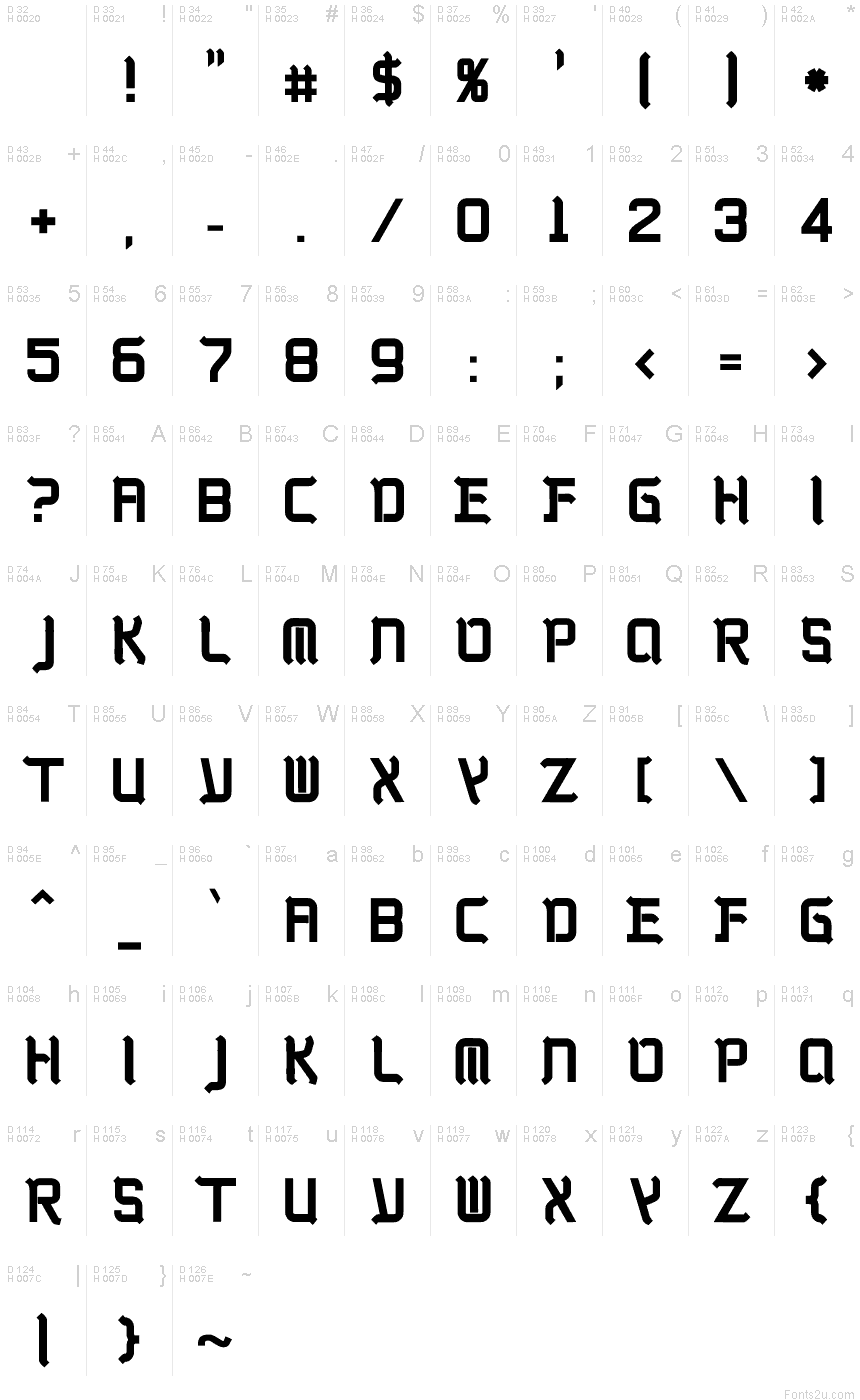
Písmo Kwadryga od flashFONT 2000 je bezplatný, moderní gotický font s ostře lomenými tvary a pevnou, vertikální strukturou. Opakující se špičaté řezy a hranaté tvary vytvářejí v textu vytesaný rytmus, díky kterému působí slova jako jeden kompaktní celek.
Kwadryga se hodí na koncertní plakáty, loga kapel, obálky fantasy knih i herní tituly, stejně jako na obaly či grafiku na oblečení. Pivní etikety a nadpisy na plakátech jsou další přirozenou volbou, když design vyžaduje ostrý gotický akcent bez zbytečných ozdob.
Kwadryga